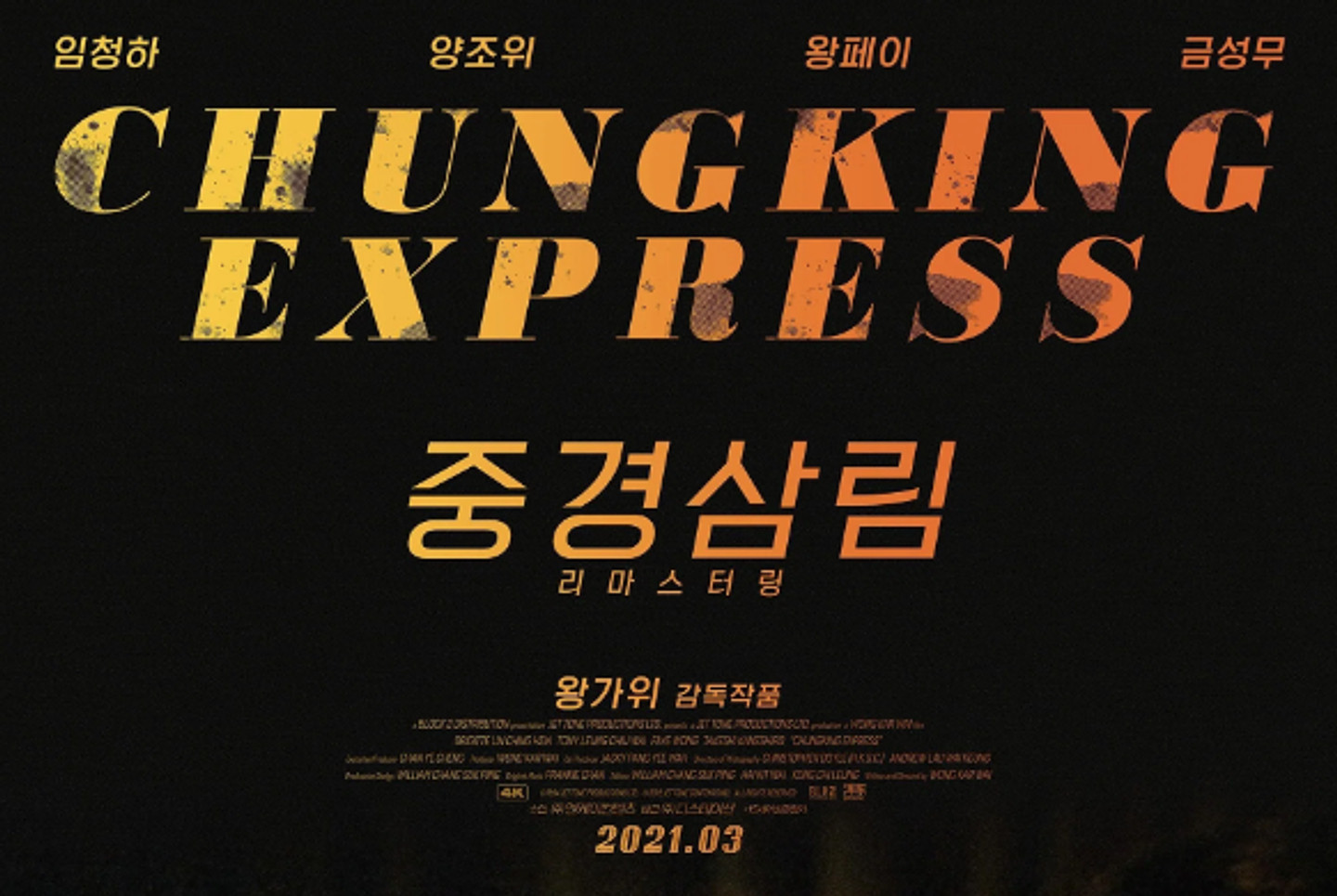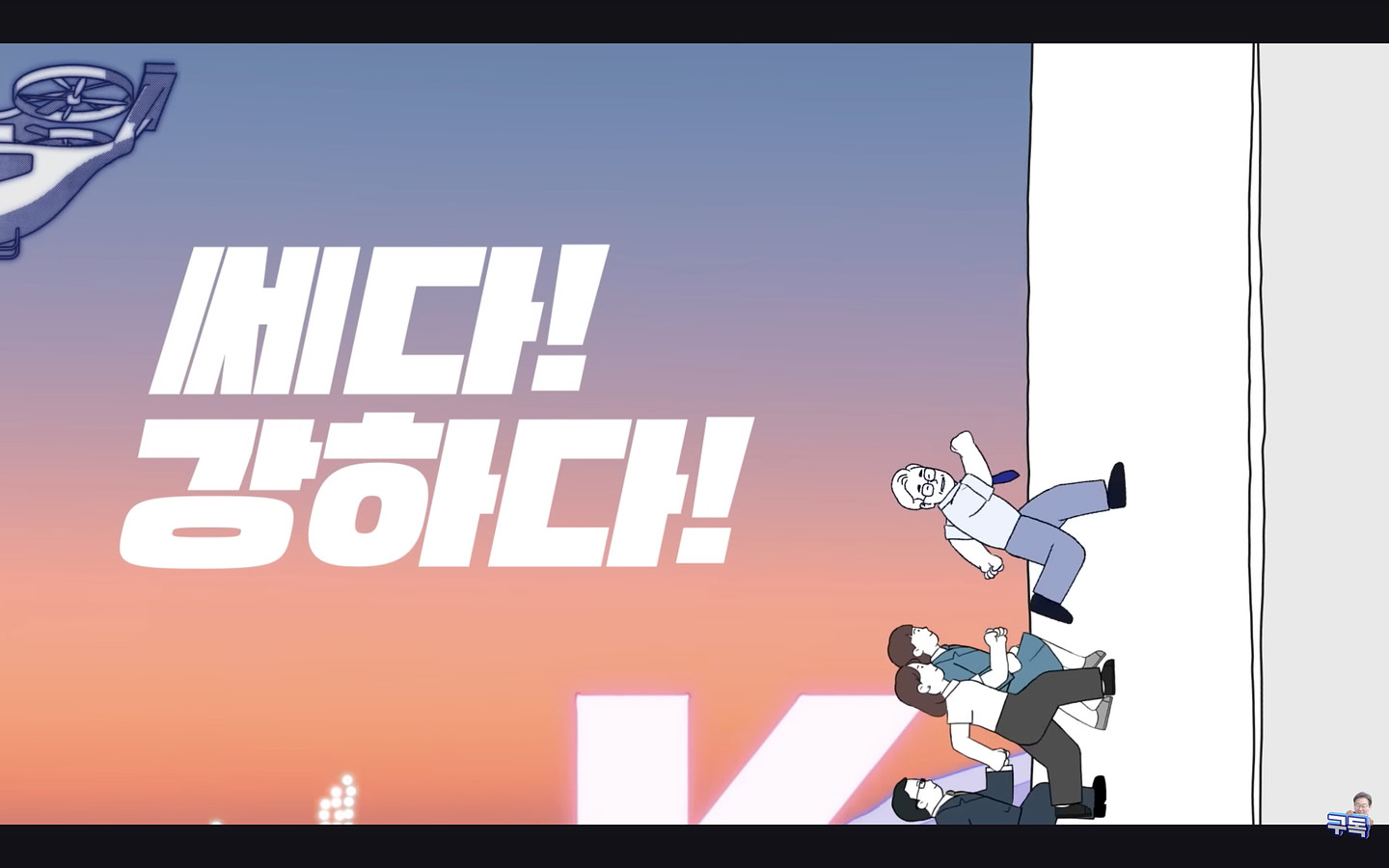
"건강한 내 삶을 지켜줄" 이랑 "건강프렌즈" 각각 글씨체 알려주세요!!
인스타에서 봤는데 폰트가 뭘까요?
전에 작업하면서 봤던 폰트를 대략적인 기억으로 그려봤는데 이 형태와 가장 가까운 폰트가 있을까요? 제 기억이 맞다면 잠깐 일하던 곳에서 산돌 클라우드가 깔려있던 것 같습니다.
폰트 뭔지 알 수 있을까요?
Sk 와이번스 시절 마킹 폰트가 궁금합니다. 만약 없다면 비슷한 폰트라도 알려주셨으면 감사할것같아여
폰트 찾을 수 있을까요? 그냥 인터넷에서 주운 이미지인데.. 괄호가 완전 둥그스름 형태가 아니고 살짝 각이 있는 특징이 있습니다 ㅠㅠ
혹시 어떤 폰트인지 아실까요?ㅠㅠㅠ